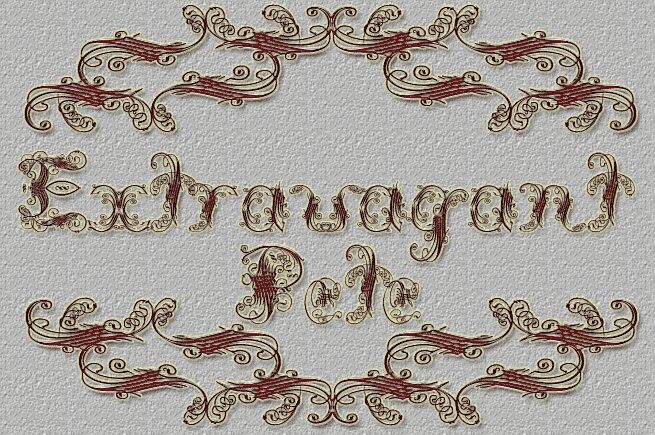
Extravagant Pete di The Mighty Pete è un font display decorativo gratuito. Ogni lettera è composta da riccioli sottili, anelli barocchi e ghirigori a inchiostro che ricordano le filigrane vittoriane disegnate a mano. I tratti si intrecciano e brillano, creando una texture ornata che trasforma ogni parola in un'opera d'arte; per questo motivo, il font dà il meglio di sé quando gli si lascia spazio per far respirare le sue curve.
L'uso di Extravagant Pete in piccole e drammatiche dosi trasforma titoli e nomi in veri pezzi da novanta: ideale per poster gotici, copertine di libri fantasy, branding ispirato al mondo dei tatuaggi, packaging ricercati, insegne teatrali o inviti opulenti. Questo font gratuito è perfetto per frasi brevi impostate in grande, mentre il testo principale può essere composto con un carattere serif o sans serif per creare il giusto contrasto.